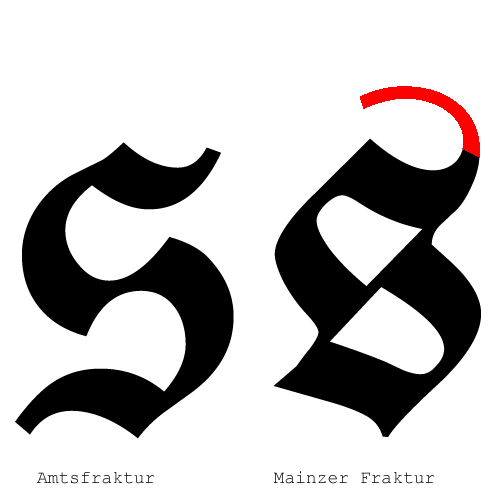
Wie nenne man den (rot gefärbten) Teil des Rund-s? Schwänzchen, Cauda, Elefäntchenrüsselchen?
Ich benötige eine Bezeichnung, um beschreiben zu können, was (unter anderem) das Rund-s der Amtsfraktur von dem der Mainzer Fraktur unterscheidet.
Das möchte ich den kleinen s der meisten Frakturschriften nicht antun, dass ich von ihren trumpesken Tollen schreibe. (Und hätte die Amtsfraktur dann eine Glatze?)
Viele Buchstabenbestandteile sind nach menschlichen Körperteilen benannt: Scheitel, Hals, Schulter, Arm, Bauch, Taille, Schenkel, Bein, Fuß. Trotzdem widerstrebt es mir von Tolle zu sprechen. Sonst noch Vorschläge?
Fällt das nicht auch in die Kategorie "Rüssel"? Ich sehe bei Deiner Graphik direkt hörend ein trööööörööööööööö 🙂
Rüssel wird ja hier der vordere Teil genannt
Das fände ich dann missverständlich, wenn der Begriff für mehrere Teile verwendet wird. Obwohl er hier tatsächlich gut passt … Einen guten Vorschlag außer Aufschwung oder Ähnliches hätte ich aber auch nicht. :-?
In Philipp Stamm: »Schrifttypen verstehen Kombinieren« sind zwar auf den Seiten 50/51 alle möglichen Körperteile als Fachbezeichnungen für Teile von Buchstaben zu finden, von Scheitel, Auge, Ohr, Nase, Hals, Kinn runter über die Schulter zum Arm, das Rückgrat bis runter zum Bein (der Rüssel ist übrigens nicht dabei). Aber dieses Schwänzchen kommt dort leider auch nicht vor.
Elefantenrüssel verbinde ich typografisch nur mit Versalien. Deswegen schrieb ich eingangs scherzhaft Elefäntchenrüsselchen.
@Schnitzel Wäre es denn überhaupt, wenn man den Buchstaben handschriftlich schriebe, ein Aufschwung? Oder ist nicht vielmehr der geschwungene Ansatz mit dem man zum Scheitel (gemäß Kathrins Wortgebrauch) übergeht?
Aufschwung, Abschwung, Anschwung, Schnörkel? Vielleicht sollte ich beim Begriff Schwänzchen bleiben.
Es fiele mir gewiss leichter zu schreiben das Schwänzchen an der Oberseite des Rund-s, als wenn ich einen Buchstaben beschreiben müsste, dessen Schwänzchen aus seinem Schenkel erwächst. Warum eigentlich diese Verkrampftheit, nur weil eine sexuelle Konotation entstehen könnte?!
Elefantenrüssel verbinde ich typografisch nur mit Versalien
Finde ich jetzt arg dogmatisch. das "Schwänzchen" wurde doch nicht aus Versehen so genannt. Warum sollte man das Teil nicht dort Elefantenrüssel nennen dürfen, wo es formal noch besser passt?
Ja, es mag dogmatisch erscheinen, doch assoziiere ich mit Elefantenrüssel tatsächlich nur die Ansätze an den betreffenden Majuskeln.
Schweif: Das sind für mich die Zierschwünge an Script-Schriften. Beim gezeigten Rund-s ist das Schwänzchen ja auch eine Art Zierschwung. Das würde also meines Erachtens gut als Bezeichnung passen.
Wäre es denn überhaupt, wenn man den Buchstaben handschriftlich schriebe, ein Aufschwung?
Da der Schwung ja nicht dem Duktus der Breitfeder folgt und Frakturschriften eigentlich (meines Wissens) reine Druckschriften sind, ist dieses Element typisch gezeichnet. Wollte man sowas mit der Feder nachempfinden*, würde man wohl die Feder auf die Kante drehen und den Zug nach oben rausziehen. Von daher, ja!
* Nachempfinden weil dieser Schwung eigentlich nicht aus dem Schreibfluss entsteht. Im Gegensatz zum Elefantenrüssel bei den Majuskeln.
Ich habe mal in zeitgenössischen Büchern geblättert (wegen eines Fraktur-Online-Workshops hatte ich die gerade parat):
Hier sieht man einen ganz leicht geschwungenen Aufschwung von Gottfried Pott (Erste Hilfe und Schrifttraining, Hermann Schmidt)
Bei Christopher Haanes ist es noch geschwungener, aber immer noch aus dem Schriftfluss:
Hier geht der Schwung wieder deutlich zurück, also nach hinten. Das kann man mit Fingerakrobatik hinbekommen. Was ich in letzter Zeit aber von Christopher Haanes oft sehe, ist sogenannte Touch-up-Kalligrafie – irgendwie zwischen Kalligrafie und Lettering. Es hat einen gewissen Schreibfluss, aber viele Details werden nachträglich mit der Federkante ausgebessert und verfeinert. Da kriegen die auch solche Schwünge hin, die erstmal sehr spontan aussehen …
Dann ist es schwer zusagen, ob es noch ein echter Aufschwung, auch wenn die Dynamik deutlich nach oben zeigt.
Hier sieht man diese Touch-up-Geschichte ganz gut:
Und wie wäre es mit Rute?  Bei Schweif fallen mir Pferde ein, und da ist das ja eher etwas herunter hängendes, Spricht man aber bei Hunden von Rute.dann sind das Rassen, deren hintere Wirbelsäulen-Verlängerug eben zumeist im Idealfall genau die Form hat, wie hier beim kleinen s: Aufsteigend und in einem eleganten Schwung über den Körper (des Hundes wie des Buchstabens)  gebogen, eher spitz auslaufend.